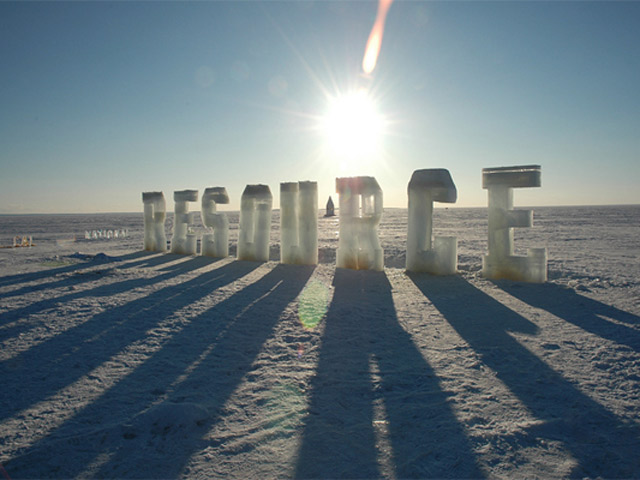
Typografie aus Eis icetypography_08
Nicole Dextras stellt Schriftzüge aus Eis in die Landschaft. Zwischen 40 Zentimetern und 2,5 Metern sind diese große, Haltbarkeit je nach Wetterlage.
„Ice Typography absorbs light, melts and eventually leaves no trace; these words have more in common with dreams and oral stories than linear language.“